中文の古本を眺める(6)『辞海・語言文字分冊』
6冊目は、上海辞書出版社の『辞海(修訂本)・語言文字分冊』。1978年4月発行、定価0.45元。92ページ。
中国で発行されている大型辞書『辞海』の分冊版の一つで、この「語言文字分冊」には言語や文字についての項が収録されている。例えば、下の画像は文字学カテゴリの中の1ページ。
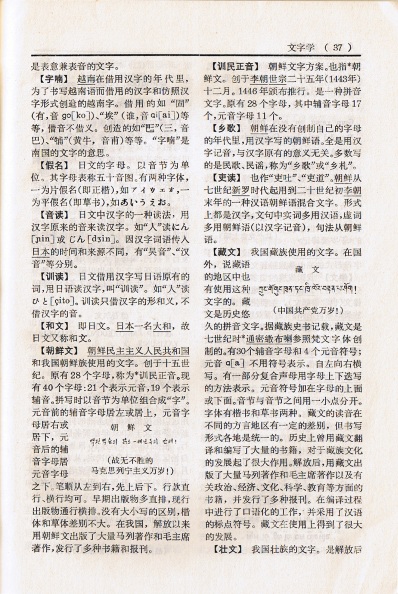
本文は明朝体で、一般的な横組み。簡体。ゴシックの見出しは【】で括られている。「越南」「李朝」「世宗」といった固有名詞には、下線(「専名号」とよぶ)が引いてある。
また、項目として立てられている語が文中に出てきた場合には、参照できるように*がつけられている。例えば、右段1, 2行目には「也指*朝鮮文。」とある。 日本の横書きの場合、註*1などにはこんな感じで語句の後ろに印をつけるが、この本では語句の前。
ただ、ハングルの例文が 战无不胜的马克思列宁主义万岁!
*2 だったり、チベット文字の例文が 中国共产党万岁!
だったりと、なんとも共産党テイスト。他のページにもあったので、その中からいくつか抜き出してみる。
まぁ、全てが全てこんな感じというわけではないけど。
もう一つ。語法学カテゴリの最後のページ。
中国語の文章で使う約物がいくつか載っており、上述の専名号もここで解説されている。書き込み*3は前の所有者によるものか。
中文での約物の使い方、基本的なところをあとでちょっと調べたい。
*1:本文中の語句や事項などについて、補足したり詳しく説明したりすること。また、その説明。(大辞林 第二版)
*2:無敵のマルクス・レーニン主義万歳!の意。
*3:【頓号】の項について、次のように書かれている。或ル部分デ日本デイフ「ナカグロ」(・)ニ相当ス ナカグロソノモノハ間隔号(・)トシテ別ニ存在ス